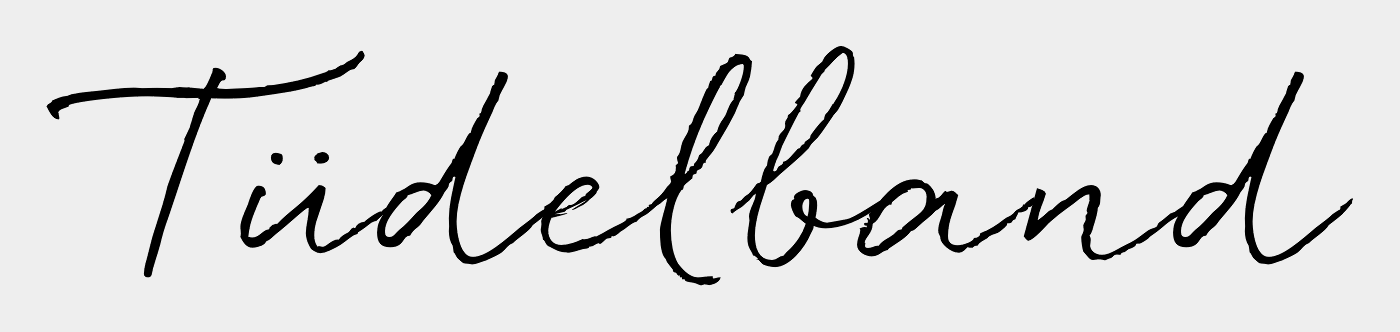
Font in Seil-Optik
ich bin auf der Suche nach einem Font, der einem Faden, Seil o.Ä. ähnelt.
Diesen möchte ich für eine Broschüre nutzen, der Studenten als Leitfaden dient.
Und eben diesen "Leitfaden" möchte ich in den Headlines visualisieren.
Wenn man "Font Rope" oder sowas googled, kommen einige Freefonts.
Ich hätte aber schon ganz gerne etwas, das "professioneller" ist.
Buchstaben-Alternativen, damit man ein wenig spielen kann wäre schon ganz schön.. ;)
Wenn ich mich richtig erinner, gibt es hier schon einen thread, in dem einige Seil-Fonts gepostet wurden. Die Suche findet ihn nur leider nicht …
Hier die Myfonts-Suchergebnisse bei “thread”. Auch bei den Ergebnissen mit “rope” dürfte ’was dabei sein.
Eine Auswahl:
Aber man könnte sich ja auch mal bei den monolinearen Scripts umsehen.
Zum Beispiel:
Toothpaste ist aber ganz schön schlecht zu entziffern. Ich habe gerade »schmerstracks« gelesen – und auch das a eher aus dem Zusammenhang erraten. Die Salty dog hingegen gefällt mir gut – sie versinnbildlicht das gewünschte Thema »Leitfaden« ganz charmant – auch wenn’s zugegebenermaßen ein leicht adipöser Faden ist.
Die Salty dog hingegen gefällt mir gut – sie versinnbildlicht das gewünschte Thema »Leitfaden« ganz charmant – auch wenn’s zugegebenermaßen ein leicht adipöser Faden ist.
Schon klar, dass die Euch maritim angehauchten Norddeutschen zusagt. ;-)
Toothpaste ist aber ganz schön schlecht zu entziffern. Ich habe gerade »schmerstracks« gelesen – und auch das a eher aus dem Zusammenhang erraten.
Ja – ging mir auch so. Fand aber die Idee dahinter bzw. den freieren Ansatz ganz nett. Man muss sicher schauen, was man damit schreiben will. Hast Du noch Alternativvorschläge?
– auch wenn’s zugegebenermaßen ein leicht adipöser Faden ist.
Dat is’ halt wat ’n ordentlicher Tampen und kein Tüdelband  :hammer:
Nur für die Drucker hier:
Tampen = kein mit Hundsleder bezogenes Werkzeug zum Einfärben des Satzes, sondern ein ordentlich dickes Seil.
Tüdelband = so was ähnliches wie Kolumnenschnur.
Hast Du noch Alternativvorschläge?
Hmmm, so ad hoc … Ich stecke im Moment noch knietief in den Entwürfen für die
Flüchtlingskinderausmalbögen, insofern habe ich leider keine Zeit für eine Recherche, aber diese beiden fallen mir spontan ein:
Wobei ich gerade sehe, dass die Quickpen teilweise unterbricht …
Ansonsten haben wir ja aber auch noch Ralfs Liste der monolineraren Schreibschriften – vielleicht ist da etwas dabei?
Ich sehe zu diesem Thema öfter mal Schriften, bei denen der »Faden« über die Grundlinie geführt wird und von dieser aufsteigt, um die einzelnen Buchstaben entweder nachzuzeichnen oder zu umrahmen. Wisst ihr, was ich meine? Leider fallen mir keine konkreten Schriftnamen ein. :-(